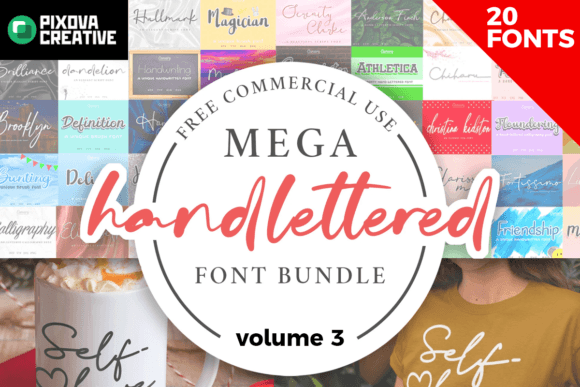
Mega Handlettered Vol. 3
Пошук відповідних елементів дизайну може бути складним, але Mega Handlettered Vol. 3 пропонує виняткову колекцію, яка миттєво покращить вашу роботу.
Незалежно від того, чи створюєте ви продукти POD (друк на вимогу), весільні запрошення або графіку для соціальних мереж, Mega Handlettered Vol. 3 стане ідеальним вибором.